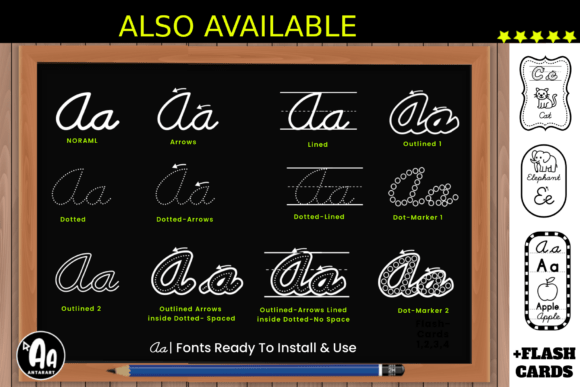
Cursive Handwriting Alphabet Tracing Set
Ulasan Lengkap: Cursive Handwriting Alphabet Tracing Set
Jika Anda mencari cara yang menyenangkan sekaligus edukatif untuk mengasah keterampilan menulis anak, Cursive Handwriting Alphabet Tracing Set adalah solusi yang tepat. Set ini dirancang khusus untuk membantu anak mengembangkan motorik halus, mengenali huruf, serta memulai latihan menulis huruf miring (cursive) dengan cara yang mudah dipahami dan menyenangkan.
- Perbaikan Keterampilan Menulis: Dengan menggambar garis bantu, anak belajar menempatkan huruf secara proporsional, sehingga tulisan tangan mereka menjadi lebih rapi dan elegan.
- Pengembangan Motorik Halus: Gerakan tracing menuntut koordinasi tangan‑mata yang akurat, sehingga membantu memperkuat otot jari dan meningkatkan kontrol gerakan.
- Pengakuan Huruf Cepat: Set ini menampilkan huruf alfabet lengkap, memungkinkan anak mengidentifikasi dan menyalin setiap karakter dengan cepat dan akurat.
- Alat Praktis untuk Guru dan Homeschoolers: Anda dapat mencetak worksheet, membuat pusat alfabet, atau merakit buku tracing sendiri. Cocok untuk kelas tradisional maupun pembelajaran di rumah.
- Dukungan Terapi Motorik: Set ini juga berguna sebagai alat bantu terapi bagi anak-anak dengan kebutuhan khusus yang memerlukan latihan motorik tambahan.
- Penggunaan Mudah dan Seru: Desain menarik dan garis bantu jelas membuat proses belajar menjadi lebih interaktif, sehingga anak tidak merasa bosan saat latihan.
Dengan kombinasi manfaat di atas, Cursive Handwriting Alphabet Tracing Set tidak hanya membantu anak menguasai huruf miring, tetapi juga membangun fondasi kuat bagi keterampilan menulis mereka di masa depan. Investasi kecil ini akan memberikan hasil yang besar dalam perkembangan tulisan tangan anak.